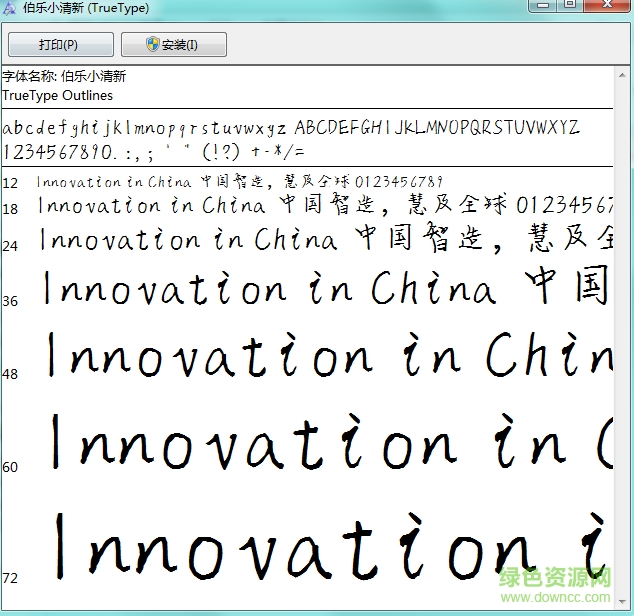
伯乐小清新体是伯乐字体系列中一款很可人很舒适的艺术字体,结合了手写体和卡通字体的风格,整体婉约清秀,很有美感,喜欢的朋友来绿色资源网即可免费下载!
伯乐小清新体有着简约清秀的美,正如它的名字,字迹清晰秀丽,深受美工设计人员的喜爱,广泛运用于艺术设计、海报设计、名片设计、广告设计等多种场合,来绿色资源网试试吧!